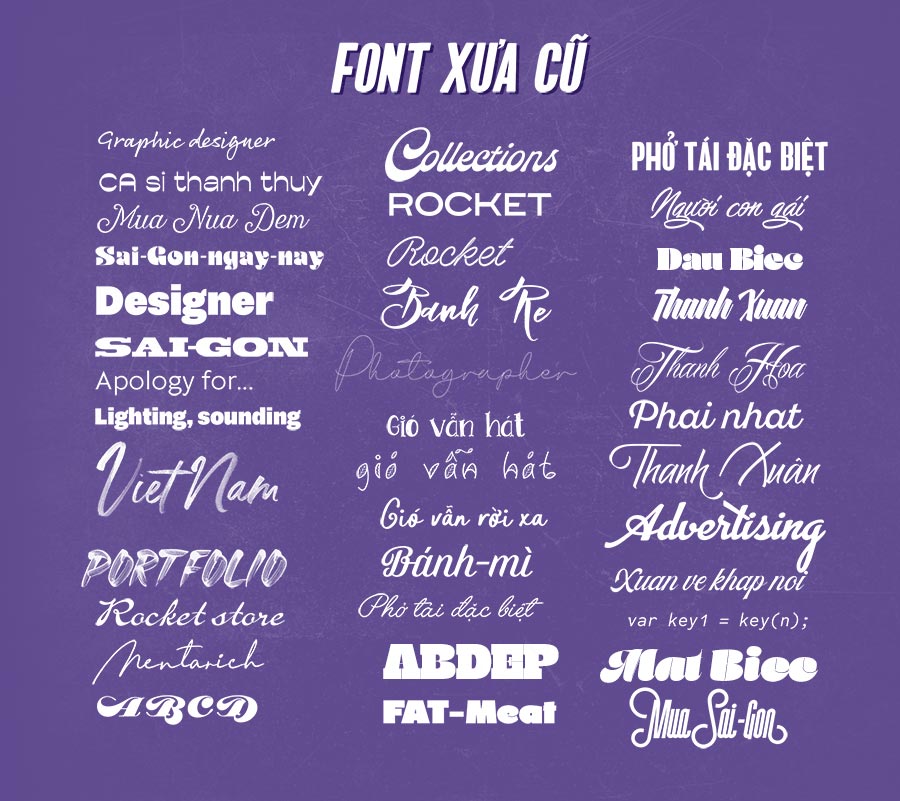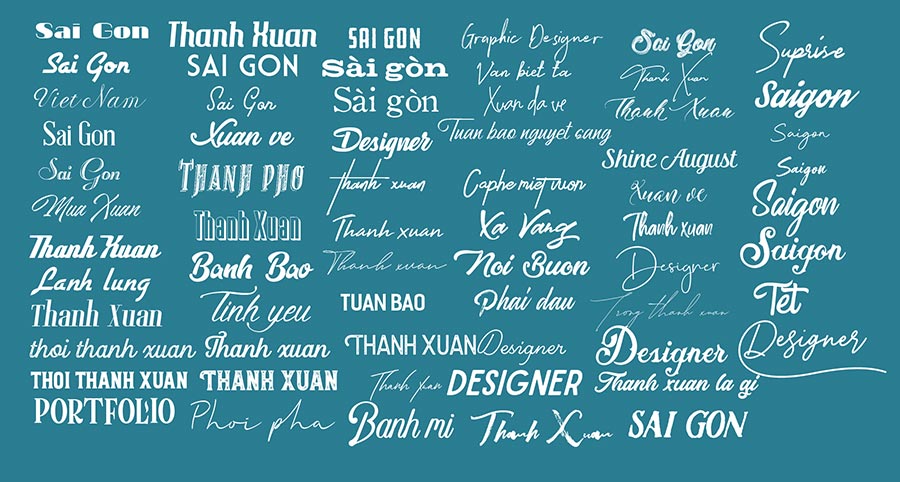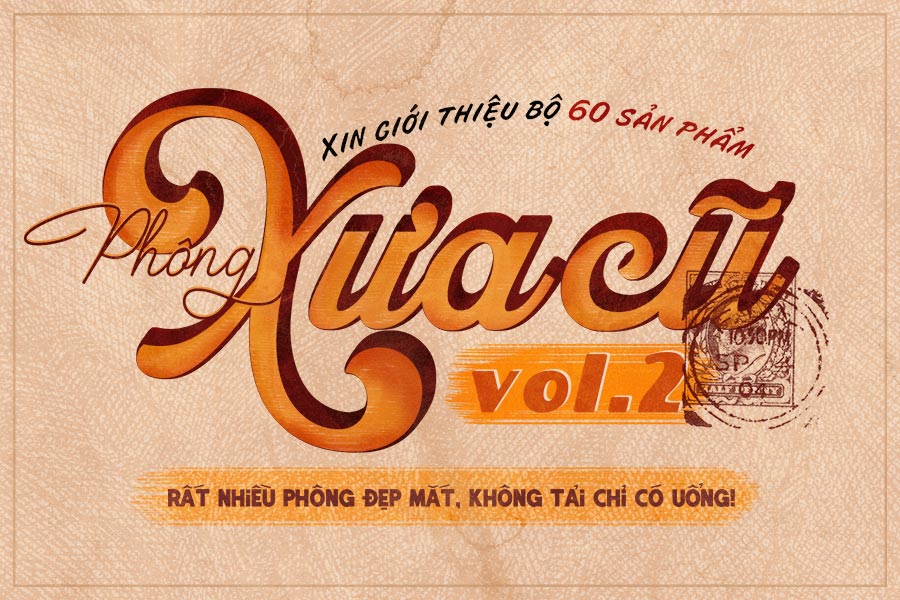
Chia Sẻ Miễn Phí 210 Font Chữ Phong Cách Sài Gòn Xưa Kèm PSD
Sài Gòn luôn là một thành phố quyến rũ, pha trộn giữa nét hiện đại và hoài cổ, đặc biệt là trong các thiết kế đồ họa. Những font chữ phong cách Sài Gòn xưa mang đến cảm giác cổ điển, đầy hoài niệm, phù hợp với nhiều dự án như thiết kế poster, bao bì, thiệp mời, hoặc các sản phẩm mang đậm dấu ấn lịch sử. Nếu bạn đang tìm kiếm những font chữ độc đáo này, bài viết này sẽ cung cấp 210 font chữ phong cách Sài Gòn xưa miễn phí, kèm theo file PSD dễ sử dụng cho các thiết kế của bạn.
Để giúp bạn dễ dàng thực hiện các thiết kế của mình, chúng tôi đã sưu tầm và chia sẻ 210 font chữ phong cách Sài Gòn xưa miễn phí, kèm theo các file PSD để bạn có thể sử dụng ngay mà không phải mất nhiều thời gian chỉnh sửa. Dưới đây là một số mẫu font bạn có thể tham khảo:
1. Sài Gòn Retro
Font chữ này mang đến cảm giác cổ điển pha lẫn hiện đại, rất phù hợp cho các thiết kế liên quan đến Sài Gòn xưa. Các chữ cái được thiết kế mềm mại, dễ đọc nhưng vẫn giữ được nét hoài niệm.
2. Sài Gòn Art Deco
Font chữ này có sự pha trộn giữa phong cách Art Deco và sự tinh tế của các bảng hiệu thời xưa ở Sài Gòn. Phù hợp cho những thiết kế yêu cầu tính nghệ thuật cao.
3. Sài Gòn Old Sign
Với thiết kế giống các bảng hiệu cũ trong thành phố Sài Gòn, font chữ này mang lại cảm giác thân quen và dễ gần, rất thích hợp cho các dự án muốn tái hiện lại không khí Sài Gòn xưa.
4. Sài Gòn Script
Là font chữ kiểu viết tay, mềm mại và tinh tế, mang đến vẻ đẹp vừa cổ điển vừa hiện đại. Đây là lựa chọn tuyệt vời cho các thiệp mời, poster hay quảng cáo mang đậm tính nghệ thuật.
5. Sài Gòn Sans
Font chữ này có các đường nét chắc chắn, dễ đọc và mang đậm ảnh hưởng của các bảng hiệu xưa. Phù hợp cho các thiết kế quảng cáo, bao bì hoặc logo.
6. Sài Gòn Brush
Với thiết kế giống như các nét vẽ tay mạnh mẽ và tự do, font chữ này mang lại cảm giác phóng khoáng, thích hợp cho các thiết kế thể hiện sự tự do, sáng tạo.
7. Sài Gòn Vintage
Được thiết kế với các chi tiết tinh tế, font chữ này rất phù hợp cho các sản phẩm liên quan đến các thương hiệu vintage, các quán cà phê cổ xưa hay các không gian nghệ thuật.